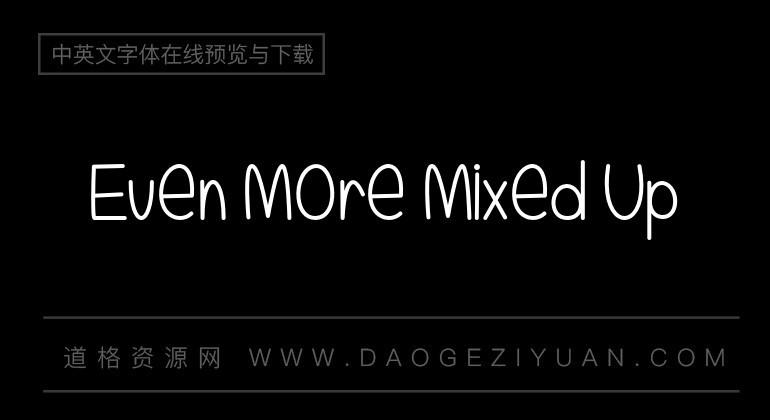
Even More Mixed Up
Even More Mixed Up 字体是一款由 Font Diner 公司设计的一款复古手写体字体。它具有复杂而多变的设计,可以帮助您创造出独特的设计效果。它可以用于各种类型的设计,如卡片、海报、书籍封面等。它的设计风格结合了复古风格和抽象风格,可以帮助您创造出独特的设计效果。它的字体细节清晰,可以帮助您创造出更加出色的设计效果。
Even More Mixed Up是一款非常不错的手写艺术字体,具有很好的视觉感,适合于文化类的宣传设计、商业类品牌的广告和产品包装设计以及个性化文字排版等较多场景。